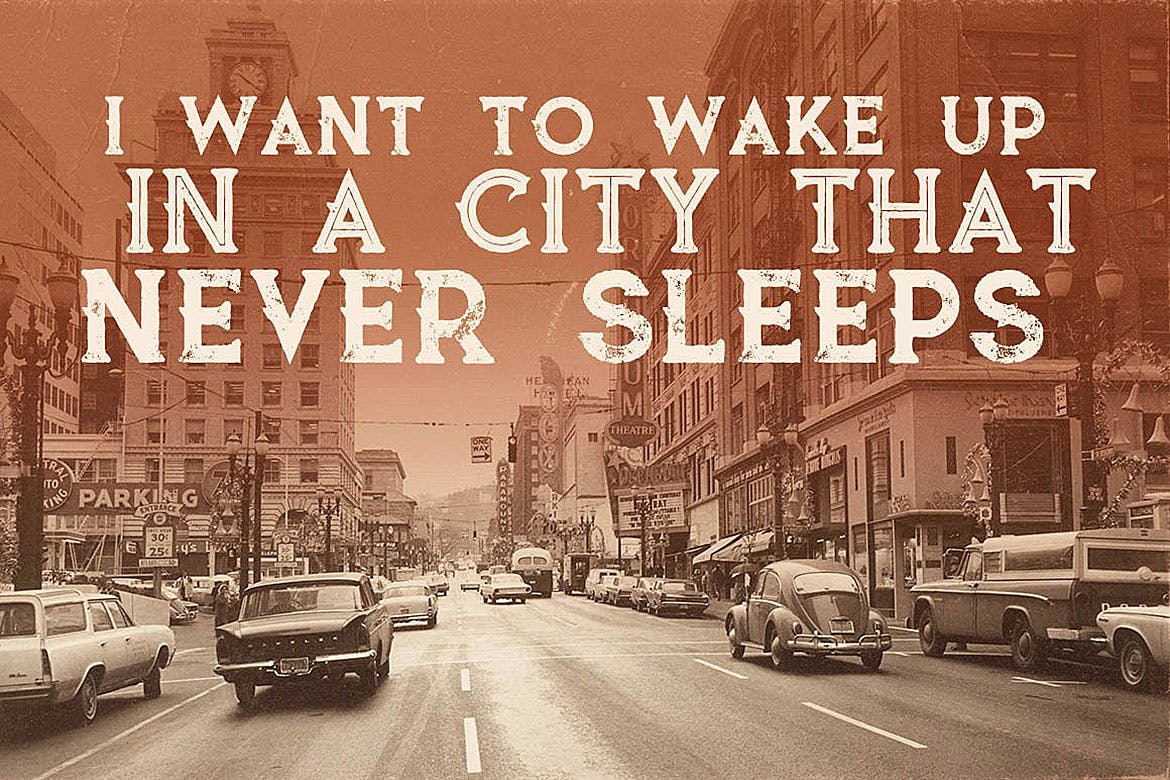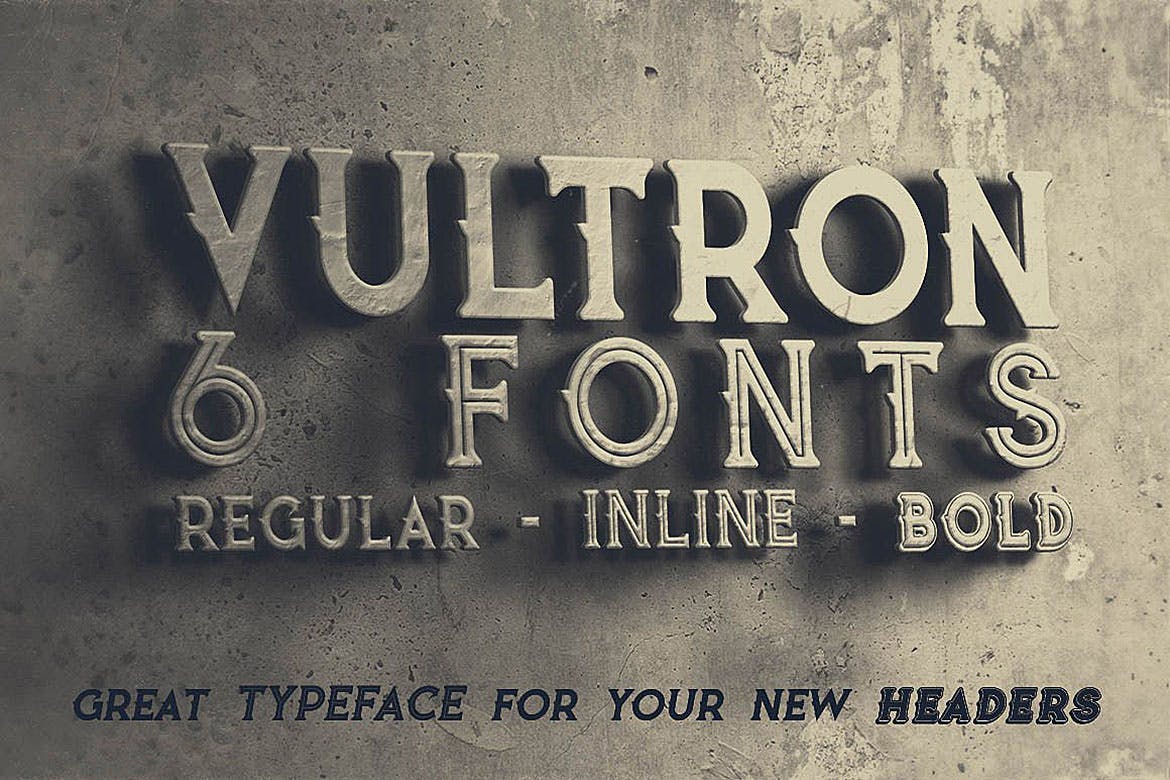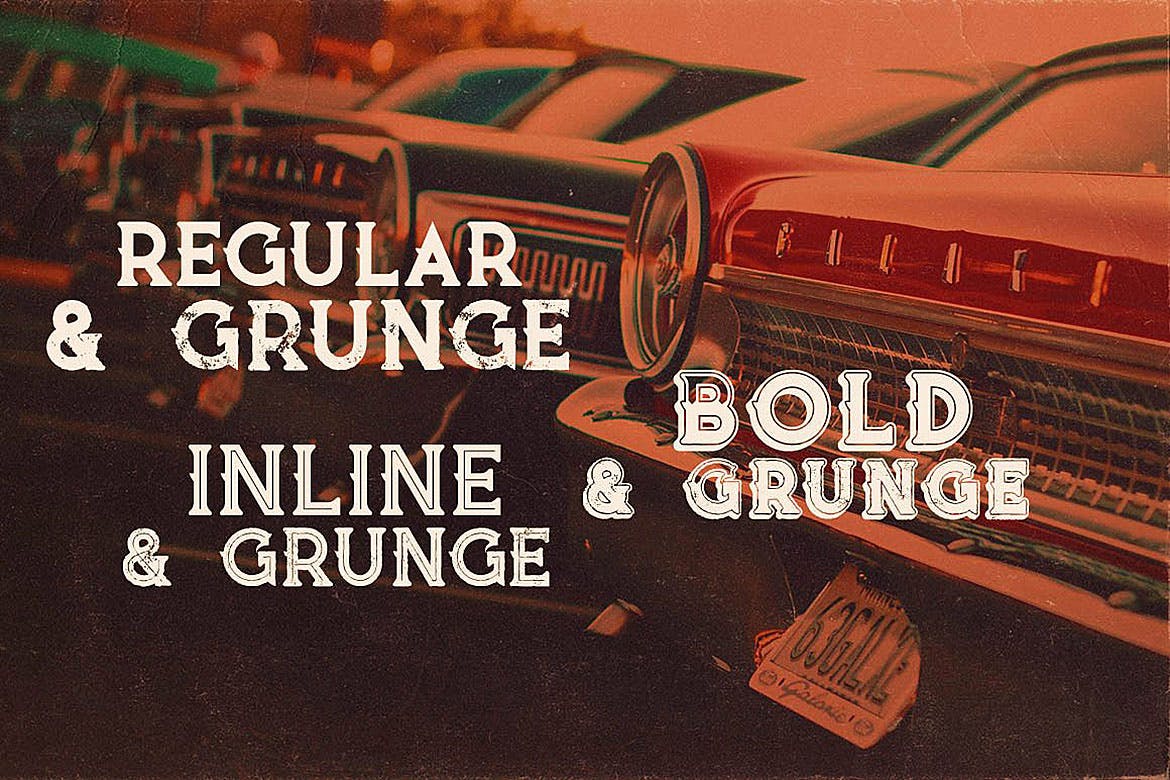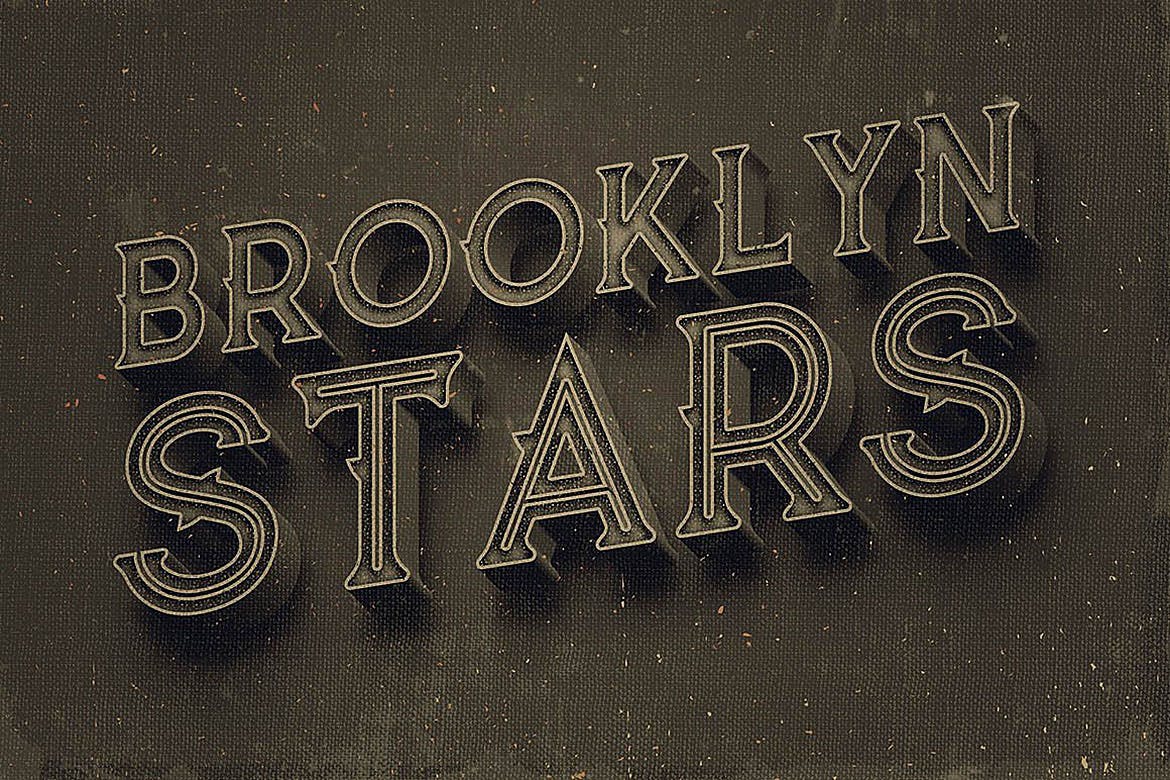
دانلود فونت وینتج و خاص Vultron
Vultron Vintage Style Font
فونت وینتج Vultron با ۶ استایل منحصربه‌فرد، مناسب برای طراحی‌های شما.
فونت وینتج و خاص Vultron یک فونت سفارشی با سبک‌های منحصربه‌فرد است که شامل ۶ استایل مختلف می‌باشد: معمولی و گرانج، خطی و خطی گرانج، بولد و بولد گرانج.